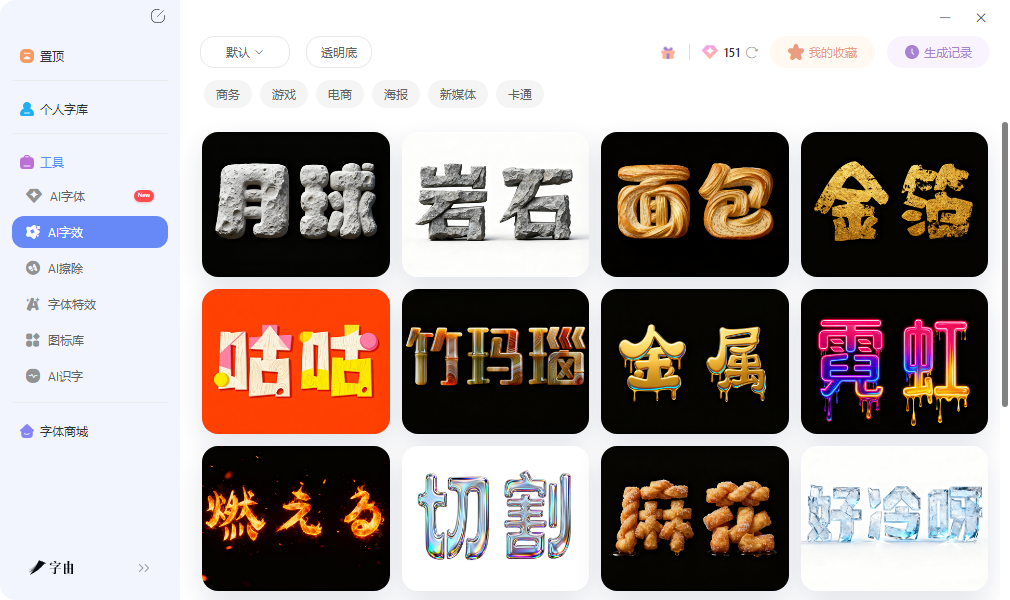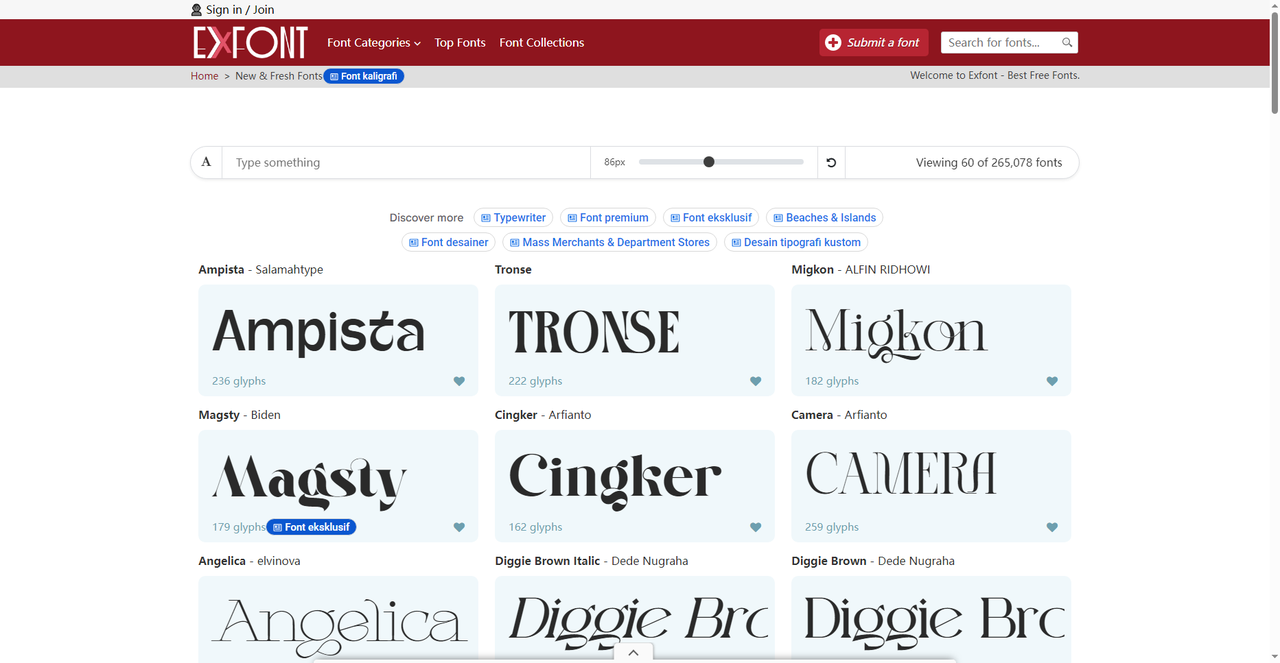
免费艺术字在线下载,海报标题不用开PS也能做
做海报、公众号封面或者活动Banner的时候,标题文字有没有设计感往往决定了整张图的视觉层次。很多人习惯打开Photoshop调图层样式,描边、投影、渐变一层层叠上去,费时费力不说,效果还不一定理想。其实有不少免费艺术字生成工具可以直接出图,输入文案就能拿到带特效的透明背景图片,拖进设计稿里就能用。这篇文章整理了五个平台,从中文AI艺术字到英文创意字体都有覆盖。
字由的AI字体功能是一款面向中文场景的免费艺术字生成工具。它提供数百种风格模板,覆盖水墨、鎏金、霓虹、火焰、立体金属、国潮等多种视觉方向。操作流程简洁,选择模板、输入文案、点击生成,三步拿到成品。产出的是透明背景PNG图片,可以直接拖进Photoshop、Illustrator或其他设计软件中使用,不需要额外抠图。
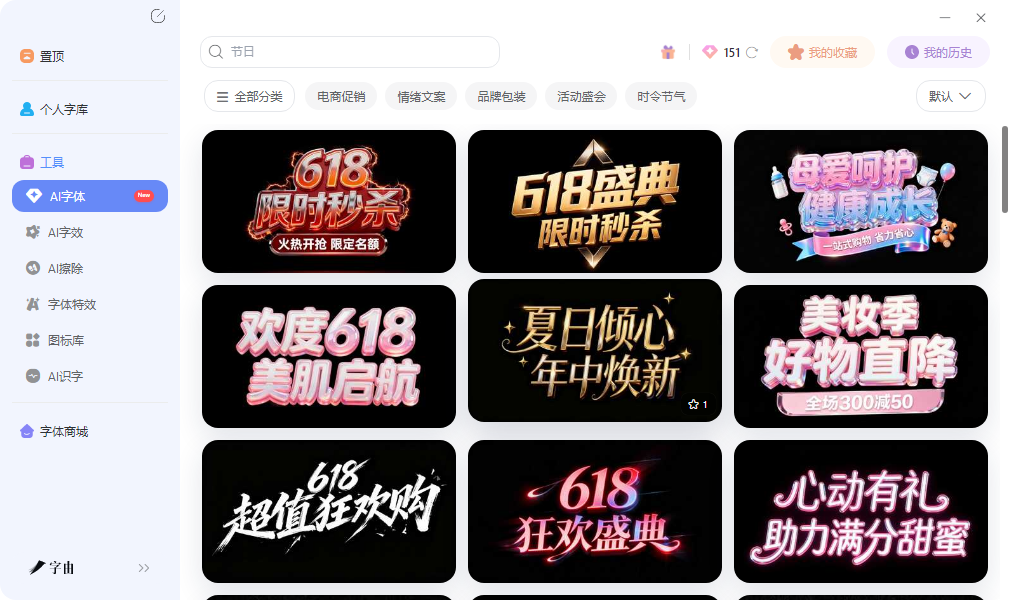
模板库的分类体系比较实用,每款模板都支持在预览区输入自己的文案查看效果,确定合适再生成,避免了反复试错的成本。
AI字效功能是另一个相关工具,和AI字体的区别在于,AI字效偏向局部特效叠加,比如给文字加发光、投影、描边等效果;AI字体偏向整体风格渲染,把整段文字变成特定视觉风格。需要注意的是,AI字体和AI字效生成的是图片而非可安装字体文件,如果后续需要修改文字内容,需要重新生成。对于海报标题、Banner文字、封面图等不需要频繁修改文字的场景,这个限制影响不大。
2、ExFont
ExFont是一个规模可观的免费字体平台,目前收录了超过265,000款字体,资源量非常大。页面顶部的预览框支持输入自己的文案,配合字号滑块可以调整预览大小,实时看到效果。这个参数化预览对判断字体在实际项目中的表现很有帮助,同样的字体在不同字号下的视觉感受可能完全不同。
平台首页展示了Ampista、Tronse、Migkon、Magsty、Cingker、Camera等多款字体,风格涵盖衬线体、手写体、装饰体等。每款字体都标注了字符数(glyphs),旁边还有收藏按钮方便后续快速找到。页面中部的标签栏提供了Typewriter、Font premium、Font eksklusif、Beaches & Islands等筛选维度,点击即可快速定位特定风格的字体。ExFont的资源量是其最大优势,265,000+款字体几乎覆盖了所有你能想到的风格。对于需要大量免费艺术字资源、喜欢在海量结果里慢慢淘的设计师来说,这个平台是一个值得长期关注的渠道。不过资源量大也意味着需要花更多时间筛选,建议配合顶部的搜索框和标签系统使用,效率会高一些。
3、FONNTS
FONNTS的特色在于对现代字体技术的支持比较全面。以截图中展示的Deuterium Variable字体为例,这是一款可变字体(Variable Font),由知名字体设计师Nikola Kostic创作,Kostic Type Foundry出品。可变字体的特点是在单个字体文件内包含了多种字重和宽度变体,设计师可以在极细到极粗之间无级调节,灵活性远超传统固定字重的字体文件。平台为每款字体提供了三个操作按钮:Download Full Family直接下载完整字体家族,Quick Try支持在线快速试用,Inspire me (AI)则通过AI推荐相关风格的字体资源。这种功能组合让找字过程更高效,下载前可以先试用确认效果,不确定选哪款时还能让AI推荐相似风格。对于寻找具有现代设计感的免费艺术字资源的用户来说,FONNTS在技术支持和功能设计方面比较到位。
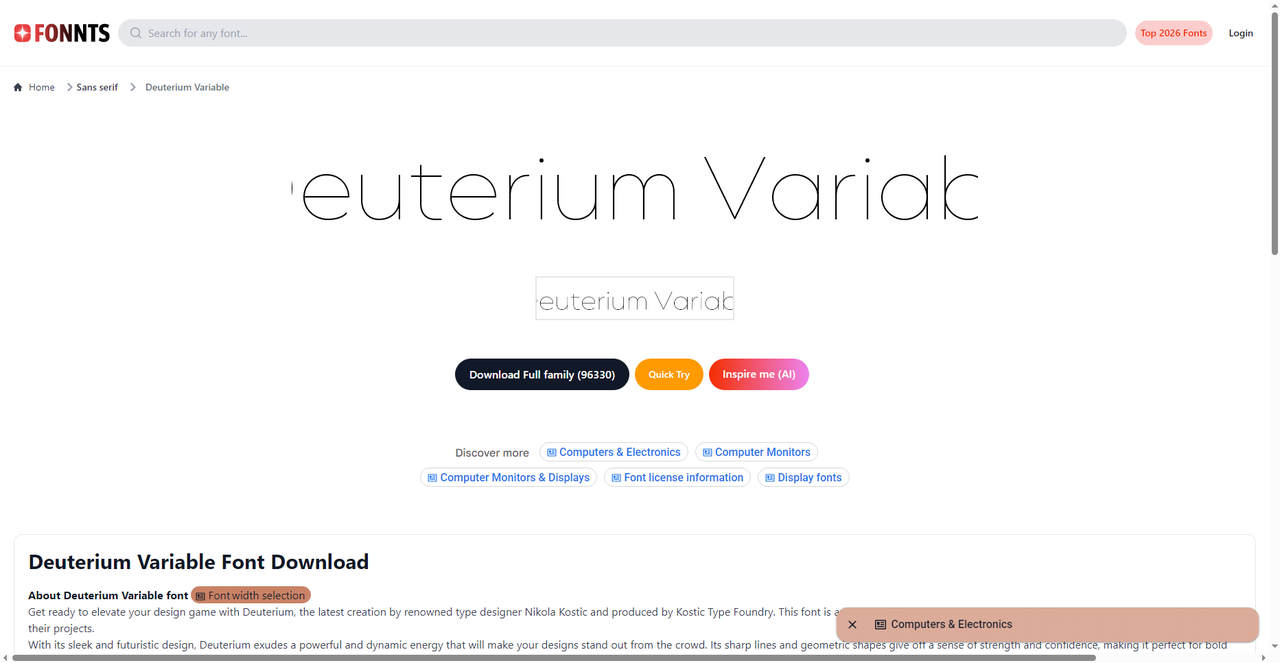
4、FontSwan
FontSwan设有专门的Variable字体专区,页面顶部的说明解释了可变字体的核心优势:动态调节字重、宽度和倾斜角度,单文件实现多种变体,在响应式设计和数字排版中表现优异。这个专区对可变字体的集中展示,让有相关需求的设计师可以快速找到适配现代网页和移动端项目的字体资源。专区展示了Arimo、Arupala Grotesk、MD Nichrome、Orbitron、Lexend、Rokkitt等多款字体。Arimo是简洁的无衬线体,适合正文和界面文字;Arupala Grotesk几何感强,适合品牌标识;MD Nichrome带有渐变光泽效果,视觉冲击力突出;Orbitron是科幻风格的展示字体,适合游戏和科技类项目;Lexend针对阅读体验优化,适合长文本排版;Rokkitt则是带有工业气质的衬线体。这种多样化的选品覆盖了不同场景的需求。
FontSwan在免费艺术字方面的价值在于,可变字体本身的技术特性就是一种"艺术"——无级调节字重可以创造出传统固定字重字体无法实现的效果,比如让标题文字从细到粗形成渐变节奏,或者在动画中平滑过渡字重变化。对于追求现代感和技术前沿的设计师来说,这里的资源值得一试。
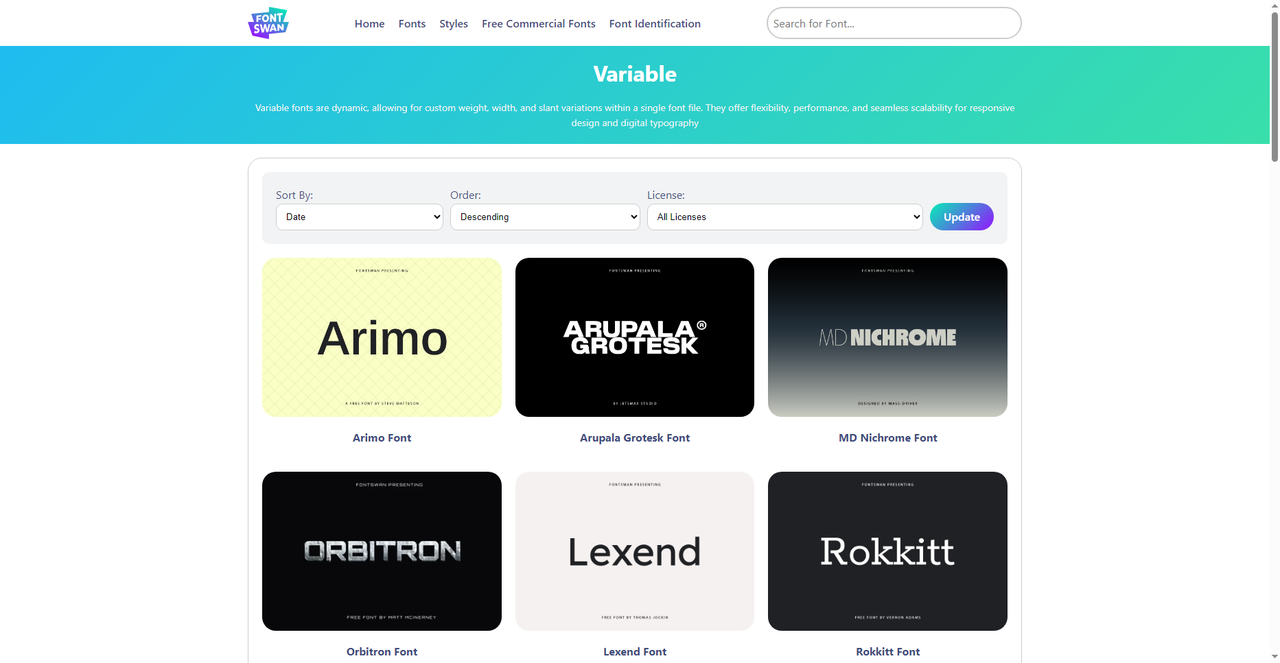
5、BFONT
BFONT的页面布局比较直观,顶部导航按Sans Serif、Serif、Display、Popular、Script、Calligraphy、Handwritten、Fancy、Techno、Gothic、Holiday等做了分类,覆盖了主流字体类型。右侧的Categories栏做得更细,3D、Basic、Brush、Calligraphy、Cartoon、Chinese、Christmas、Comic、Curly、Decorative等数十个分类都标注了收录数量,找特定风格的字体时效率较高。
BFONT的分类精细度在免费字体平台中比较突出,尤其是Holiday、Christmas等按节日划分的分类,做季节性设计物料时直接点进去就能找到氛围匹配的字体。对于需要免费艺术字资源、且偏好按精确分类逐步筛选的用户来说,BFONT的导航体系比较友好。
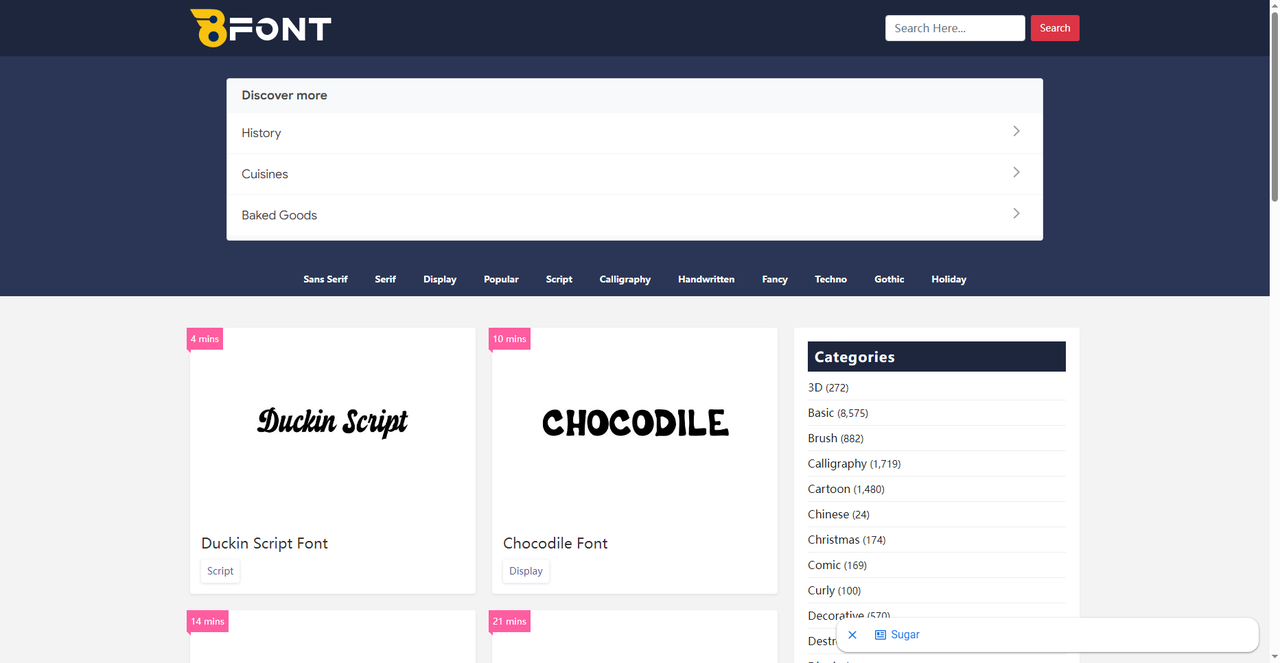
做中文海报标题和活动封面,字由的AI字体生成速度快、风格选择多,透明背景PNG直接拖进设计稿,配合每日免费算力,作为免费艺术字来源比较省心。ExFont资源量最大,适合英文创意字体的批量探索。FONNTS和FontSwan在可变字体方面技术领先,适合现代感强的设计项目。BFONT分类精细,按节日和风格筛选效率很高。五个平台搭配使用,中英文艺术字需求基本都能覆盖。